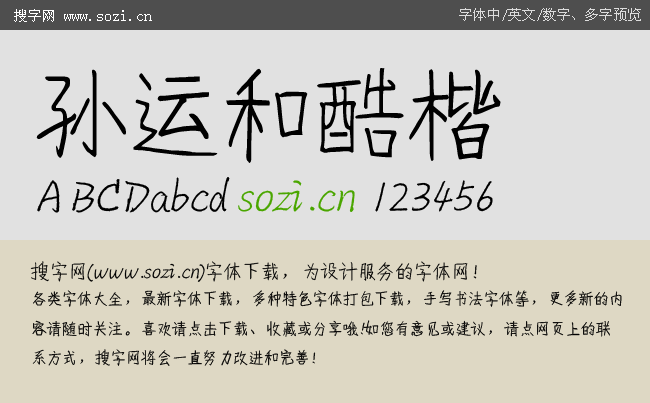
孫運(yùn)和酷楷
搜字網(wǎng)提供一款手寫(xiě)風(fēng)格的孫運(yùn)和酷楷中文字體下載,孫運(yùn)和酷楷是一款手寫(xiě)風(fēng)格的中文字體,由酷愛(ài)書(shū)法的個(gè)人字庫(kù)制作發(fā)燒友孫運(yùn)和制作,該字體略帶卡通風(fēng)格,字跡大方美觀,整體效果非常出眾,能夠適用于卡通設(shè)計(jì)、廣告設(shè)計(jì)、名片設(shè)計(jì)、包裝印刷、產(chǎn)品設(shè)計(jì)等應(yīng)用。